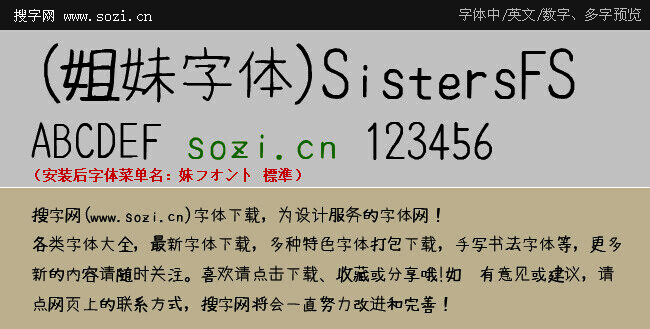
姐妹字體SistersFS
搜字網(wǎng)給大家提供一款姐妹字體SistersFS日系中文字體下載,寒蟬書體是一款手寫風(fēng)格的卡通字體。此款字體筆畫稚嫩,充滿童真,視覺效果非常有趣味性。字體適合兒童廣告設(shè)計(jì)、卡通海報(bào)設(shè)計(jì)、包裝設(shè)計(jì)等應(yīng)用。